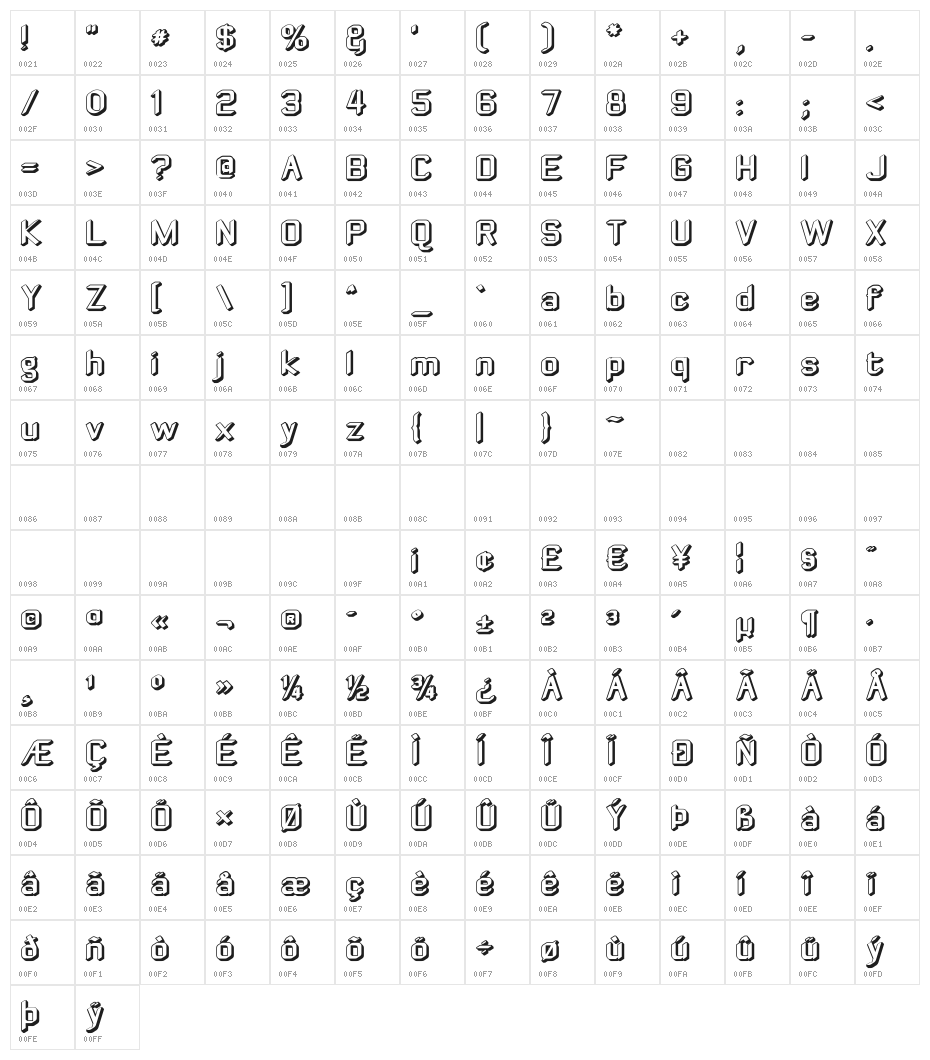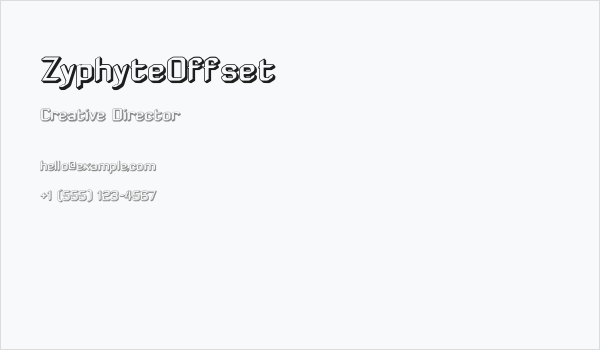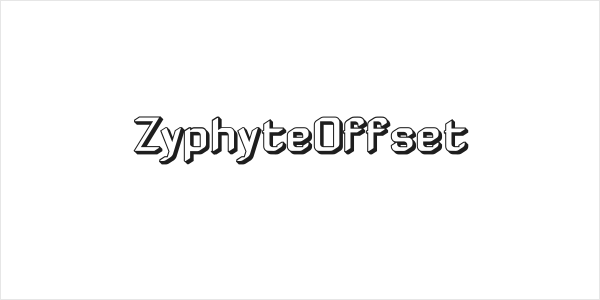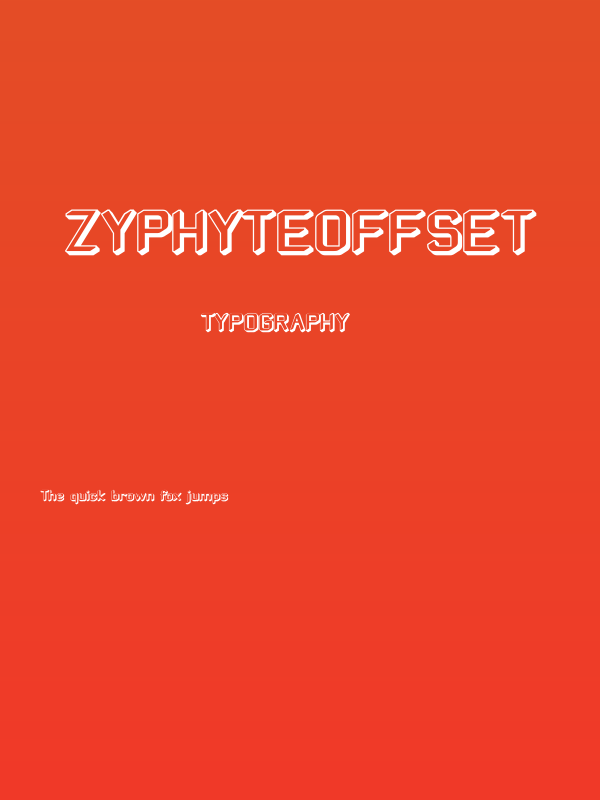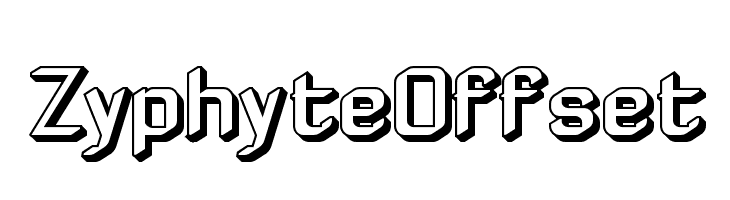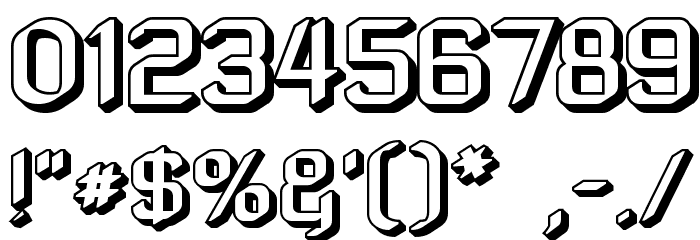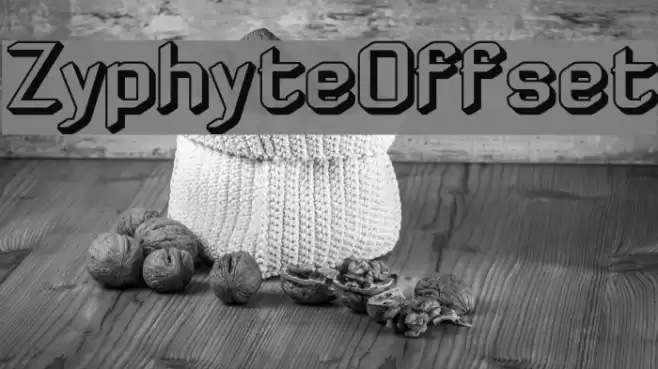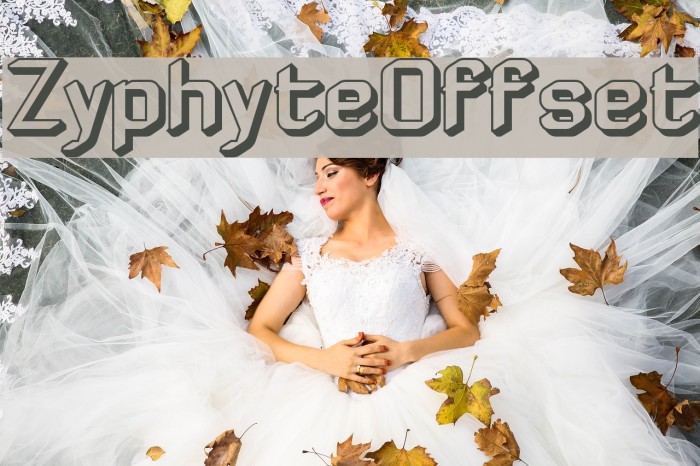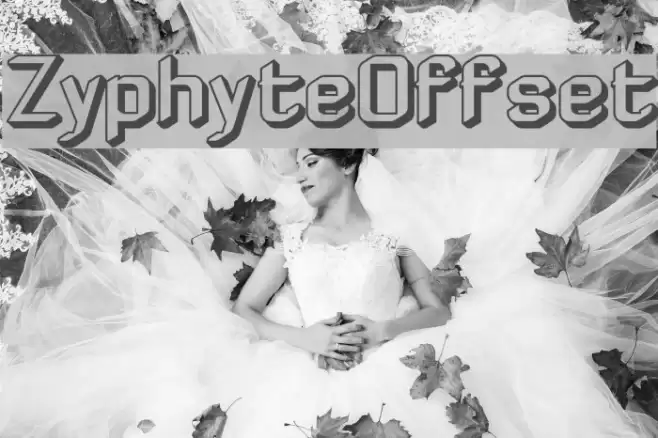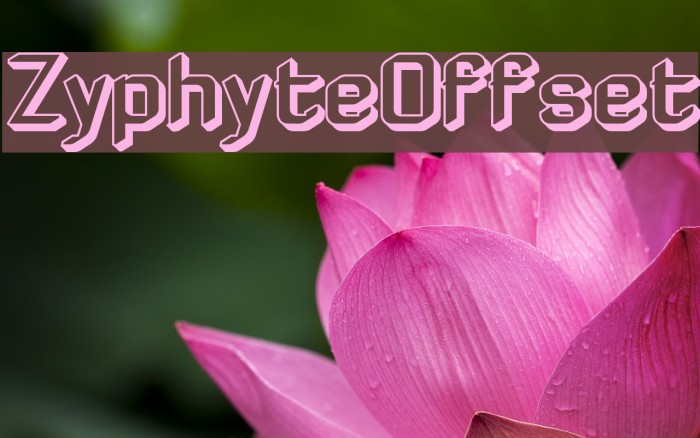
ZyphyteOffset Font
| العرض | Condensed |
| مشاريع مقترحة | Ideal for branding, poster design, video game graphics, and any project requiring a bold, eye-catching typeface. |